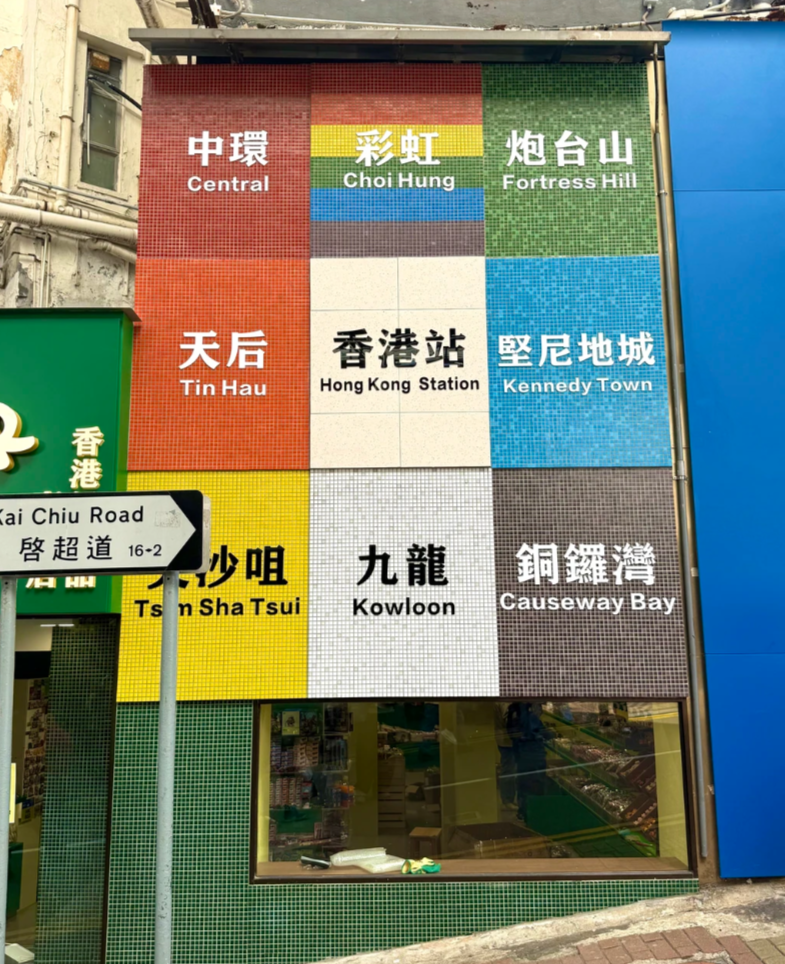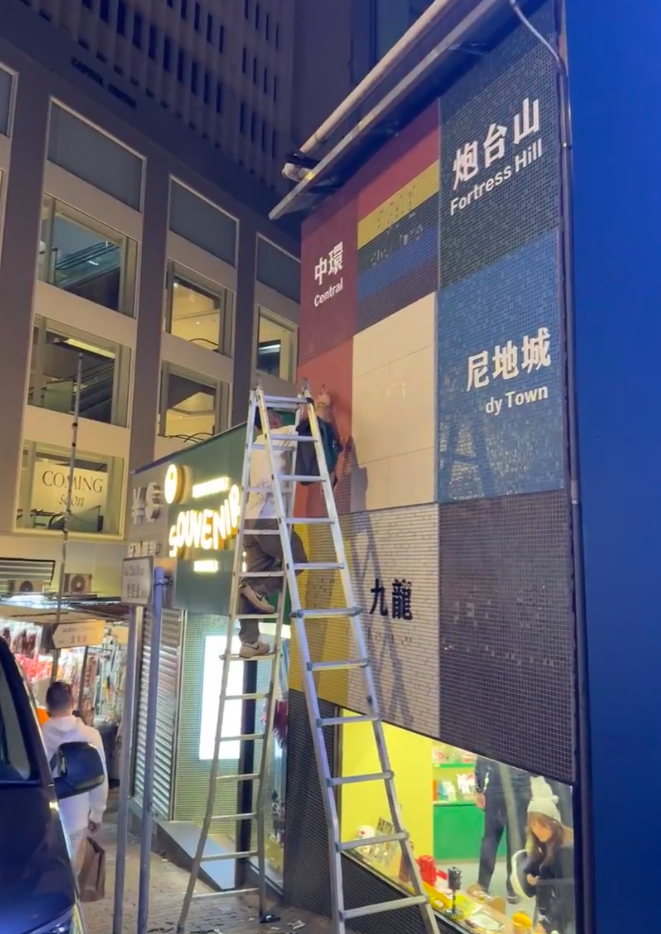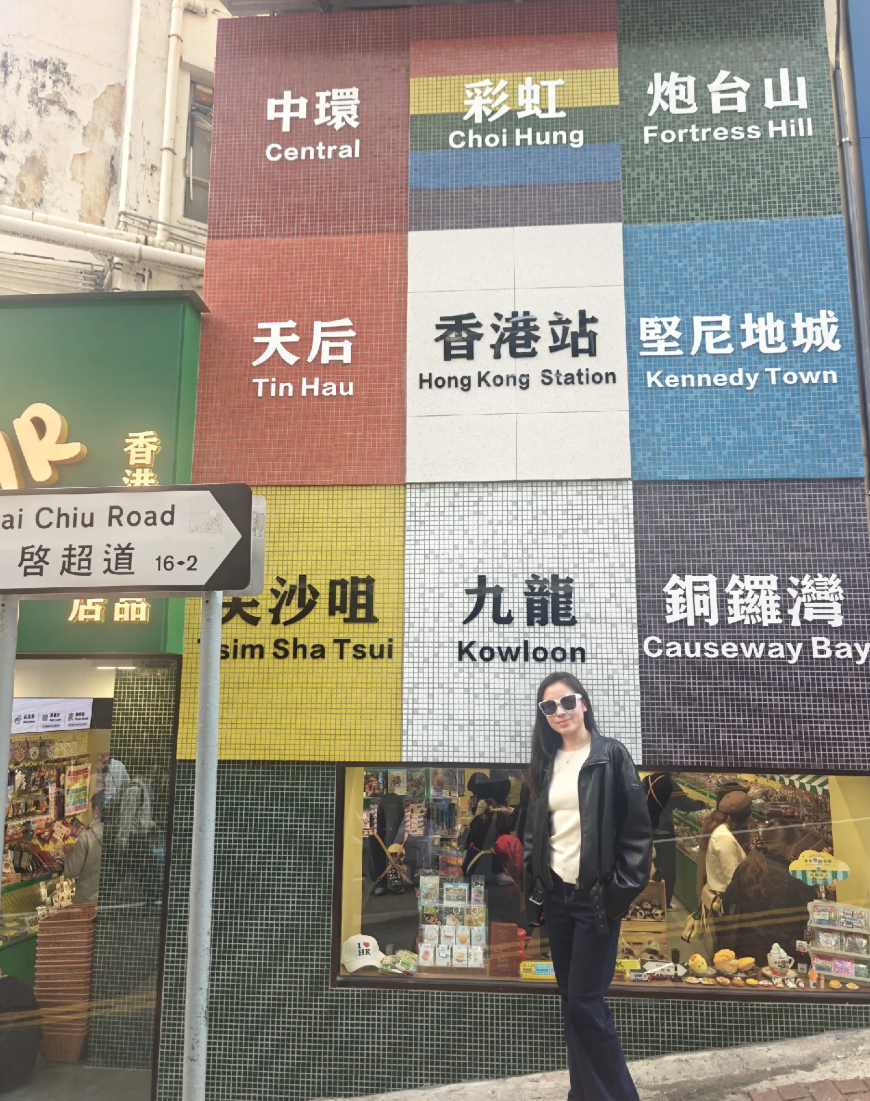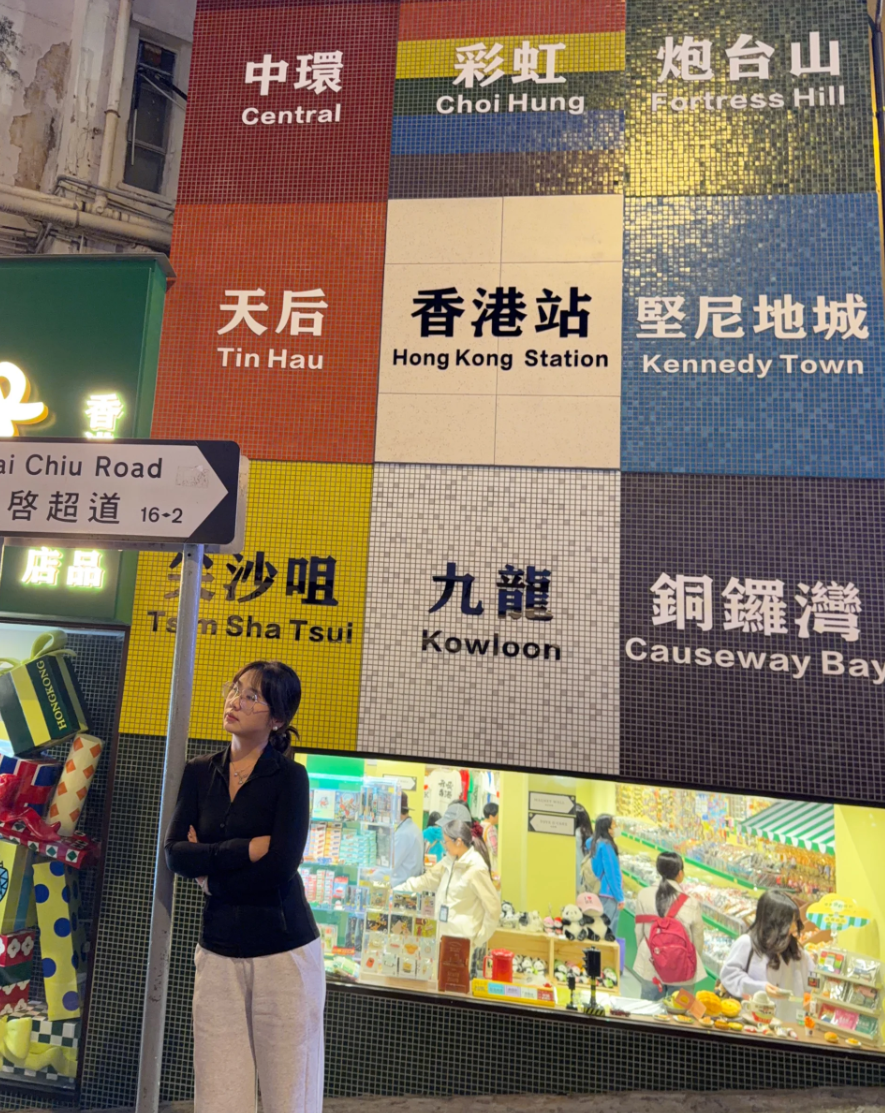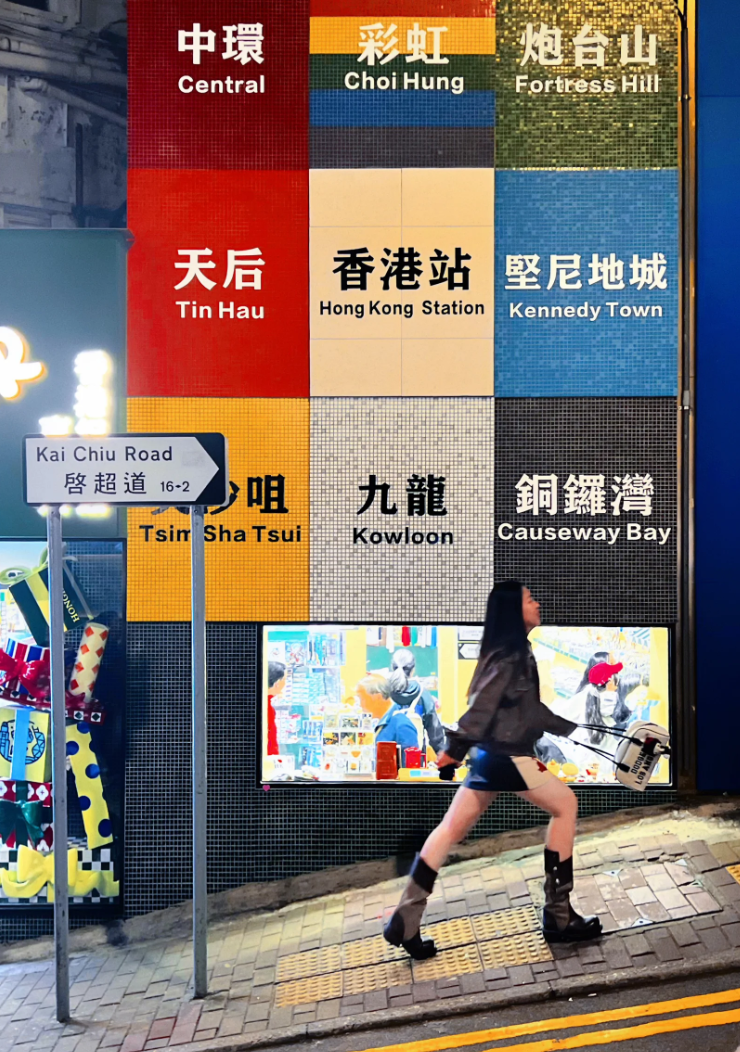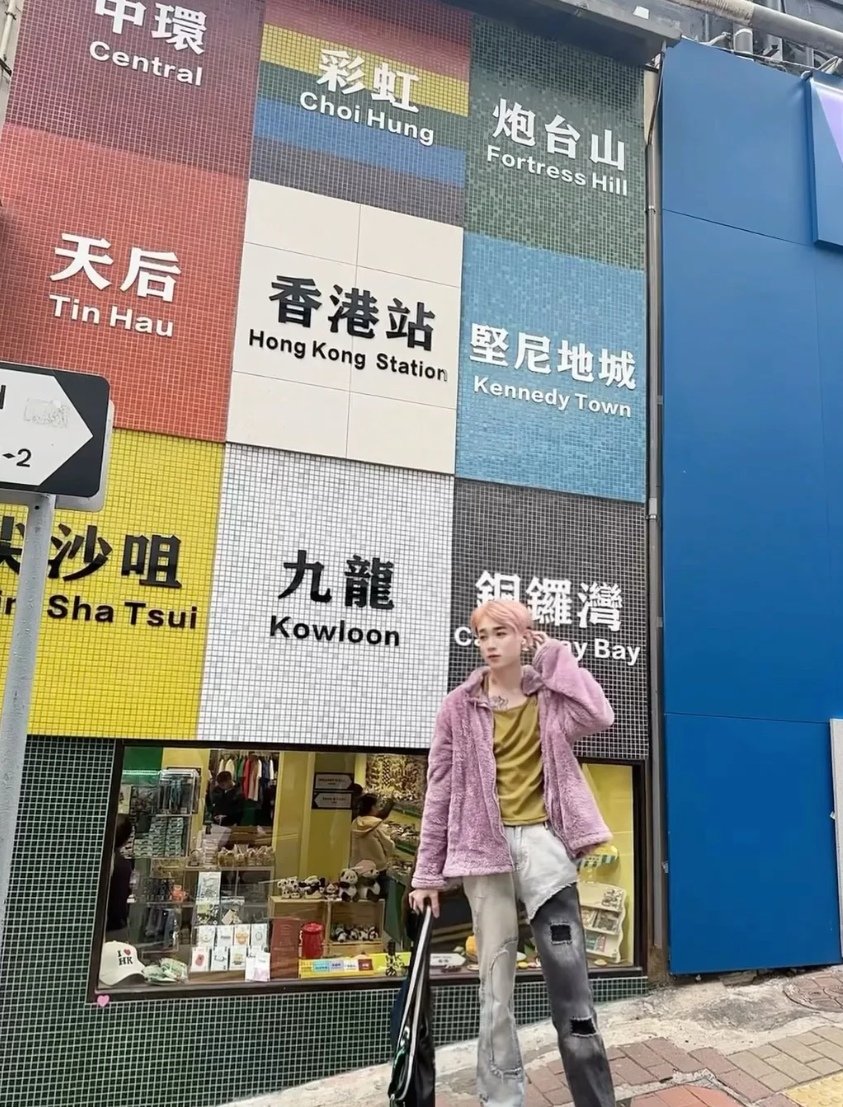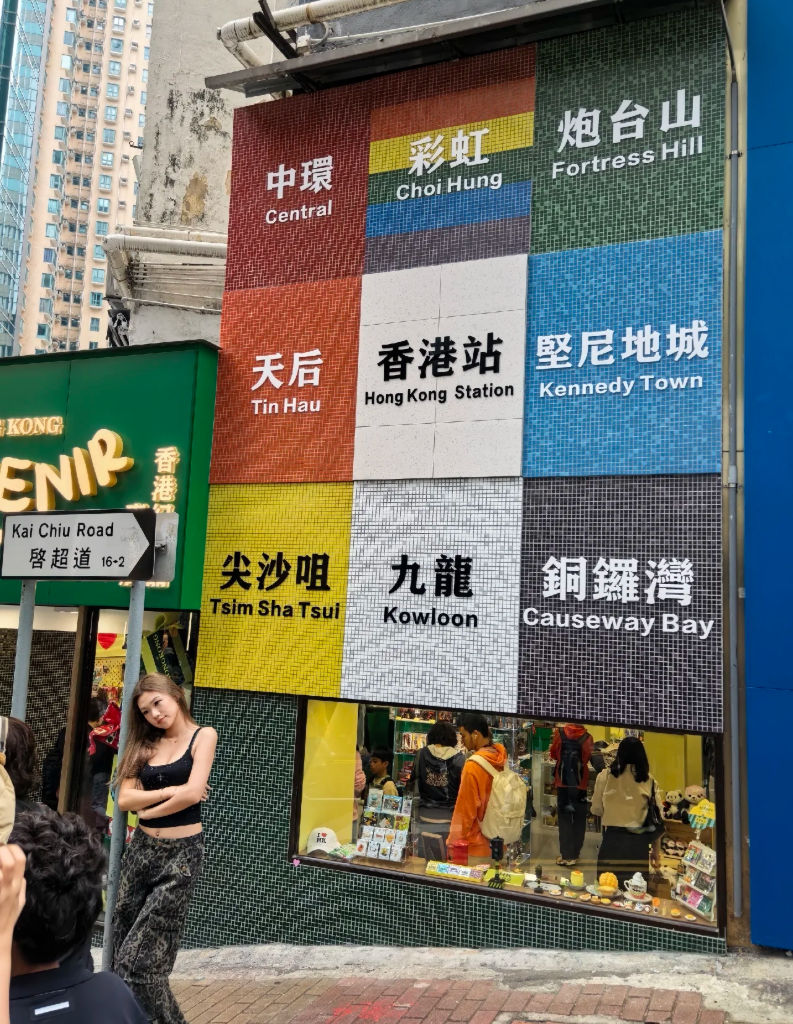
銅鑼灣街頭「港鐵月台牆」成打卡熱點 爆紅數日即拆走字體|網上熱話
銅鑼灣啓超道街頭出現一塊有港鐵多個車站字眼的「月台打卡牆」,不過數日內被拆下車站字眼。(小紅書)
不少遊客到訪香港期間,於各大港鐵站的月台拍照「打卡」成為必備行程,最近銅鑼灣街頭出現一塊有中環、尖沙咀、彩虹等多個特色車站字眼的「月台打卡牆」,於社交平台小紅書瘋傳,吸引了大批遊客「打卡」,街道更因此人頭湧湧,不過「月台牆」卻於數日後被拆下車站字眼,原因眾說紛紜。
這面「月台打卡牆」位於銅鑼灣站F1出口外附近啓超道,鄰近店舖為一間紀念品小店,牆面設計分作9格,模仿9個港鐵站內的月台牆身及顏色,有香港站、中環、彩虹、尖沙咀、銅鑼灣、天后等9個地標站。遊客不用走遍各大站即可輕鬆拍下全港代表性車站,極速成小紅書熱搜「香港免費拍照新地標」,連日更有不少遊客聚集排隊朝聖,令本身已是人流集中地的啓超道更水洩不通。
網民批評塞上加塞
不過,「打卡牆」爆紅數天後,有網民於本月10日晚發現有工人拆卸牆面,原本9個港鐵站的名字被拆走,只剩下各代表顏色,中間一格換上「I ❤ HK」,小紅書有網民留言回應「是不是被mtr告」,另有人指可能是人流太多,因安全問題拆卸,「可能阻礙交通,這條路老多人了,打卡不安全,如同堅尼地城,危險」。亦有人稱「這個創意很好,但是也太山寨了吧,如果不是路牌我真的以為這是在內地某不知名景區」、「立在銅鑼灣的板子,結果銅鑼灣的背景顏色還用錯了,字體也不對,能用點心嗎」。
另有香港網民批評「色唔啱,字體唔啱,站名都錯埋」、「平時已經夠多人….宜家塞上加塞」、「呢條街本身人流已經多,依家仲搞埋個打卡點」、「字款都唔啱,求其咗啲喎」。